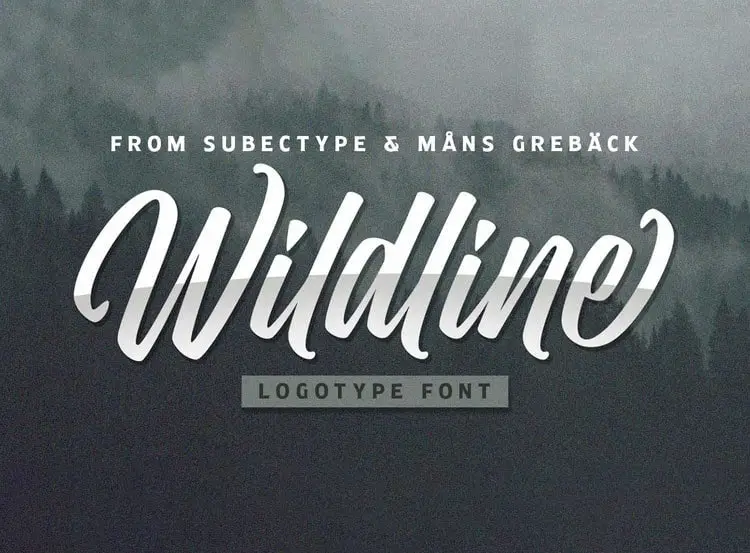
Wildline Script Font – Download Grátis
A Wildline Script Font é uma elegante tipografia moderna que oferece um toque refinado ao seu projeto. Desenhada pelo talentoso designer Mans Greback, essa fonte bold traz a sofisticação de um logotipo ou letra pintadas à mão por um pincel. Perfeita para aqueles buscando incorporar um ar autêntico e único em seus projetos visuais, seja um selo de empresa, uma página web ou qualquer outro design que exija um visual delicado e inovador. Com sua tipografia moderna e versátil, a Wildline Script Font é uma escolha inteligente para quem busca harmonia entre elegância e contemporaneidade em suas criações.